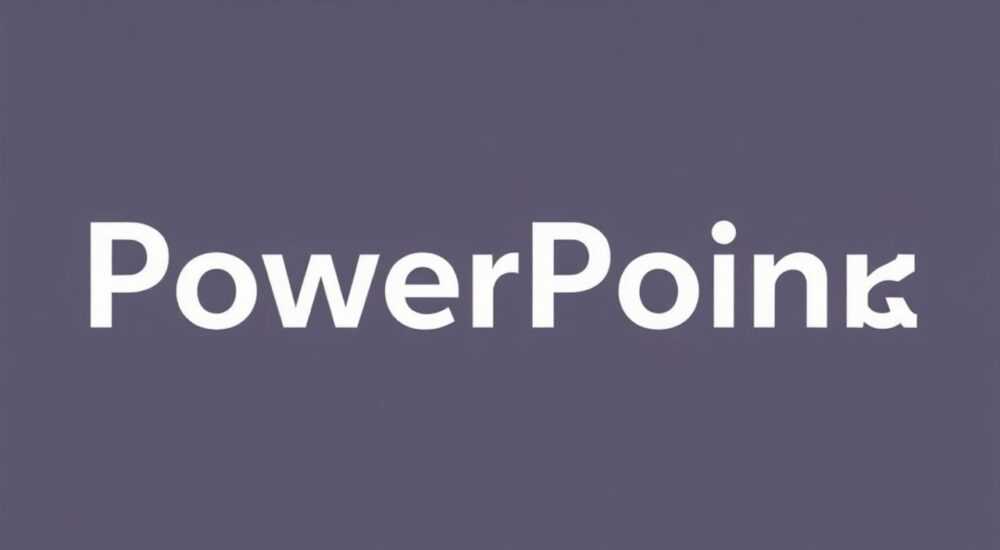
Как добавить скаченный шрифт в повер поинт
Добавление скаченного шрифта в PowerPoint — стандартная задача для дизайнеров, преподавателей и бизнес-пользователей, стремящихся к уникальности презентаций. Основная сложность заключается не в самом процессе установки, а в правильной интеграции шрифта в систему и его последующем отображении на других устройствах. Главное правило: шрифт нужно установить в операционную систему, а не просто импортировать в PowerPoint.
Установка шрифта в систему: Windows и macOS
Перед тем как использовать шрифт в PowerPoint, он должен быть установлен в операционной системе. Только после этого программа сможет его распознать. Процесс отличается в зависимости от используемой платформы, но в целом прост и занимает несколько минут.
Для Windows 10 и 11:
- Скачайте файл шрифта (обычно в формате .ttf или .otf).
- Найдите файл в проводнике, щёлкните по нему правой кнопкой мыши и выберите «Установить».
- Если у вас нет прав администратора, система предложит установить шрифт только для текущего пользователя — этого достаточно.
- После установки перезапустите PowerPoint, чтобы обновить список доступных шрифтов.
Альтернативный способ — через папку «Шрифты»:
- Откройте Панель управления → Оформление и персонализация → Шрифты.
- Перетащите файл шрифта в открывшееся окно или скопируйте его в папку C:WindowsFonts.
- Система автоматически зарегистрирует новый шрифт.
Для macOS:
- Дважды щёлкните по скачанному файлу шрифта — он откроется в приложении «Просмотр шрифтов».
- Нажмите кнопку «Установить шрифт».
- Если появится запрос на разрешение, подтвердите его.
- Шрифт станет доступен во всех приложениях, включая PowerPoint, без перезагрузки.
Проверка успешной установки
Перед переходом к PowerPoint убедитесь, что шрифт действительно установлен. Откройте любой текстовый редактор (например, Word или Блокнот) и проверьте, появился ли он в списке шрифтов. Если да — значит, система его распознала.
Добавление шрифта в PowerPoint: пошаговая инструкция
Как только шрифт установлен в системе, вы можете использовать его в PowerPoint. Процесс одинаков для всех версий программы — от 2016 до Microsoft 365.
- Запустите PowerPoint (если был открыт — перезапустите для обновления шрифтового кэша).
- Создайте или откройте существующую презентацию.
- Выделите текстовое поле или введите новый текст.
- На вкладке «Главная» найдите выпадающий список шрифтов (обычно рядом с кнопками размера и стиля текста).
- Прокрутите список вниз — недавно установленный шрифт должен находиться вверху или в разделе «Недавние».
- Выберите шрифт — текст мгновенно изменится.
Если шрифт не отображается:
- Убедитесь, что вы перезапустили PowerPoint.
- Проверьте, установлен ли шрифт в системе.
- Иногда шрифт может иметь нестандартное имя — сверьтесь с названием файла.
Использование шрифта в заголовках и основной части
Рекомендуется использовать декоративные шрифты только для заголовков, акцентов и логотипов. Для основного текста выбирайте более читабельные варианты. Даже если шрифт отлично смотрится в крупном размере, при маленьком он может стать нечитаемым.
Цель использования |
Рекомендованный тип шрифта |
Пример |
Заголовки |
Декоративный, рукописный, геометрический |
Montserrat, Lobster, Playfair Display |
Основной текст |
Гарнитуры с засечками или без (серифные/гротескные) |
Roboto, Georgia, Open Sans |
Акценты, цитаты |
Курсивные или узкие начертания |
PT Serif Italic, Raleway Thin |
Форматы шрифтов и совместимость с PowerPoint
PowerPoint поддерживает два основных формата шрифтов: TTF (TrueType Font) и OTF (OpenType Font). Оба работают корректно, но имеют различия в функциональности.
- TTF — старый, но надёжный формат. Поддерживается всеми версиями Windows и macOS. Хорошо работает в PowerPoint, но ограничен в продвинутых типографских функциях.